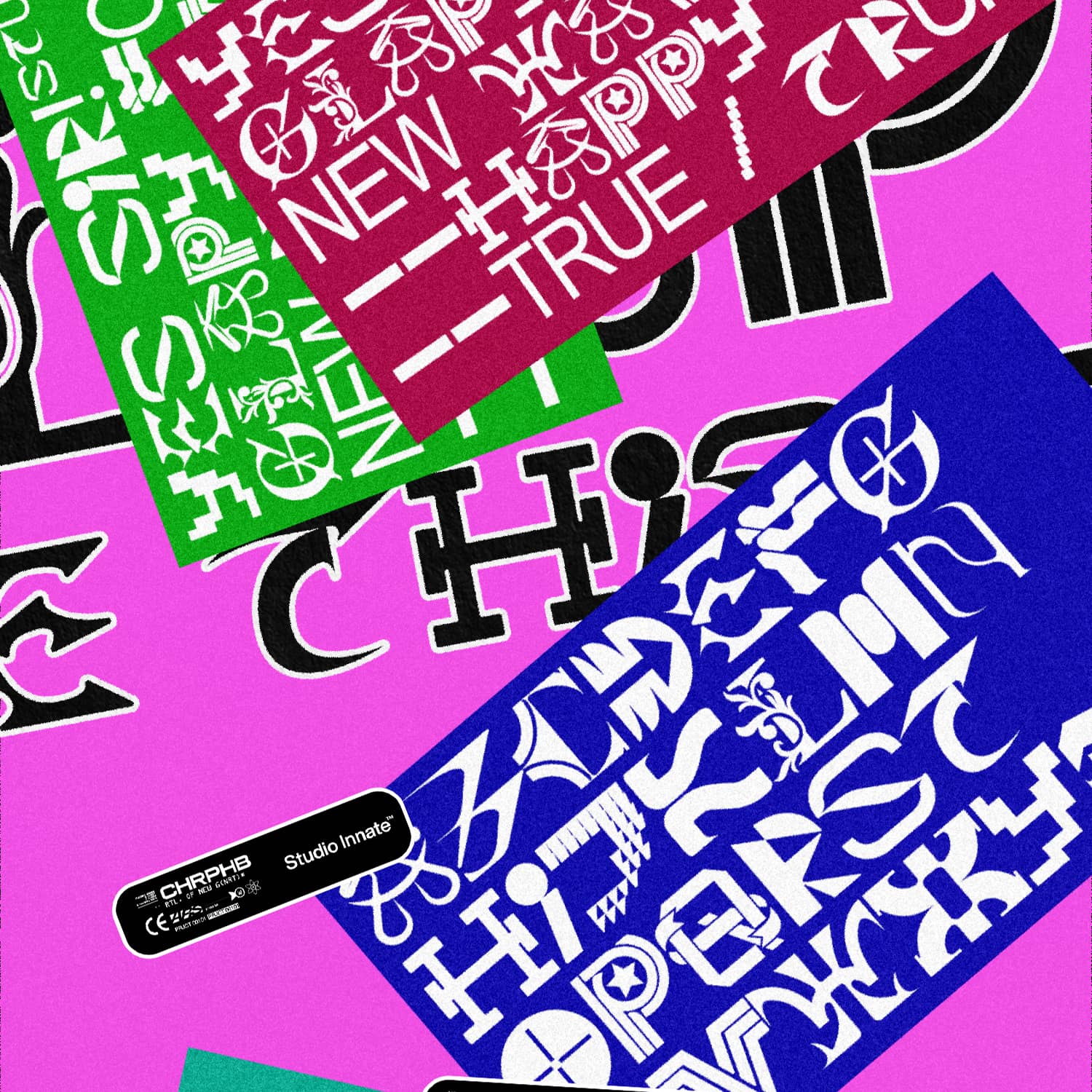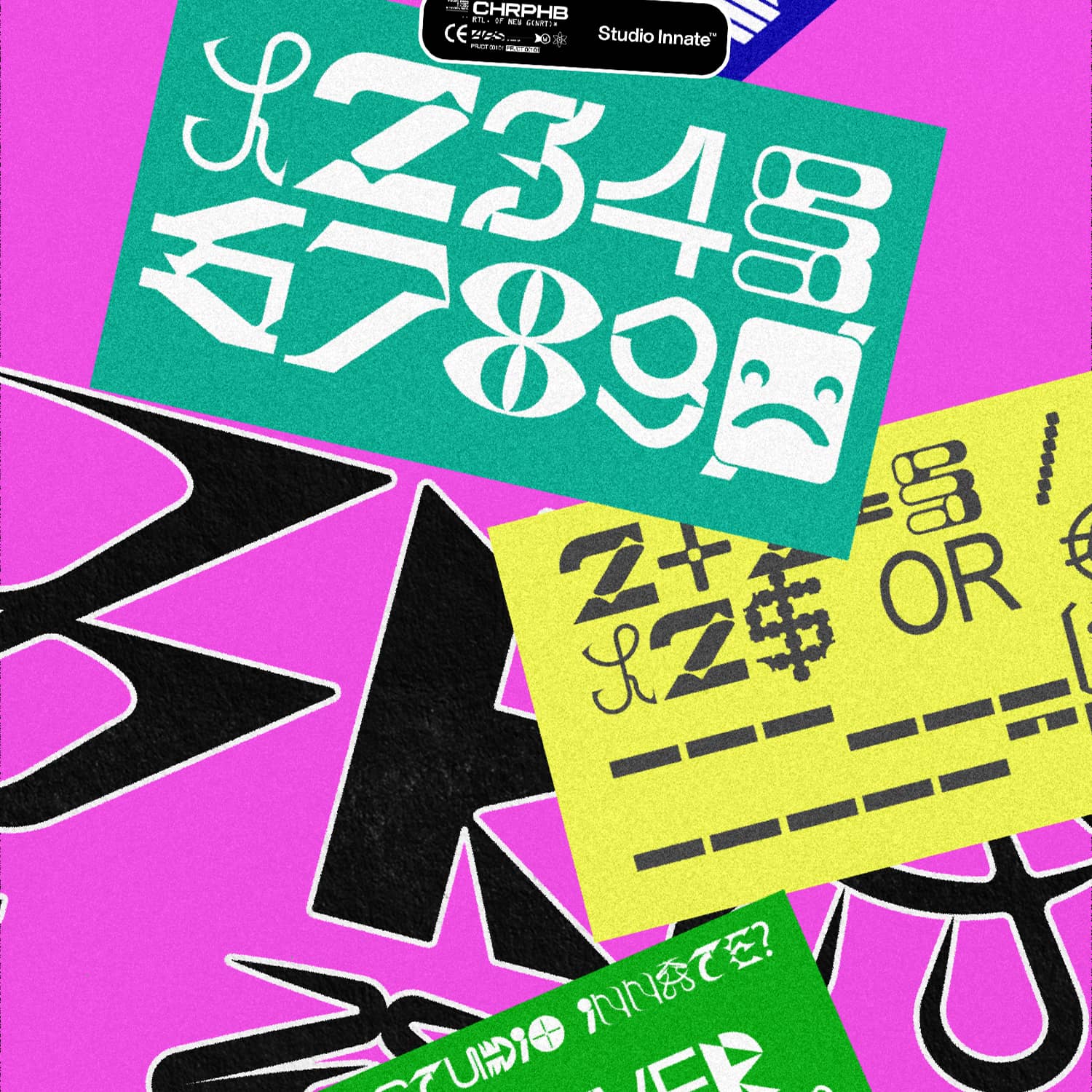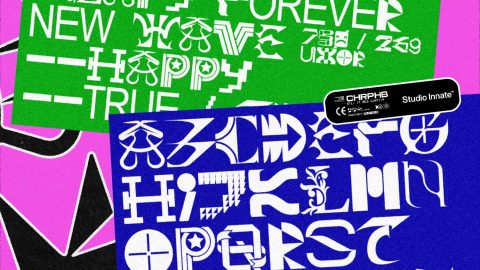
Khám phá Glapy Font , phông chữ hiện đại và vui nhộn với thiết kế “random” độc đáo. Hoàn hảo để thêm nét chơi đùa và phong cách đương đại vào mọi dự án sáng tạo của bạn!
1. Giới Thiệu Glapy Font
Bạn đang tìm kiếm một phông chữ mang lại sự tươi mới, vui nhộn nhưng vẫn giữ được nét hiện đại? Glapy Font chính là lựa chọn hoàn hảo dành cho bạn! Được phát triển bởi @chrphb, phông chữ này nổi bật với thiết kế “random” độc đáo, nơi mỗi ký tự, biểu tượng và con số đều được chế tác tỉ mỉ, mang đến cảm giác sống động và sáng tạo cho mọi thiết kế.
Với sự kết hợp giữa các chữ cái viết hoa cổ điển và kiểu dáng hiện đại, Glapy Font là công cụ lý tưởng để thêm phong cách vui tươi và cá tính vào bất kỳ dự án nào – từ poster, logo đến bao bì sản phẩm.
2. Đặc Điểm Nổi Bật Của Glapy Font
Thiết kế “Random” độc đáo : Mỗi ký tự đều có nét riêng biệt, tạo cảm giác ngẫu nhiên và thú vị.
Phong cách vui nhộn và hiện đại : Lý tưởng cho các dự án cần sự sáng tạo và năng động.
Hỗ trợ đa dạng ký tự :
- Chữ hoa (Uppercase)
- Chữ thường (Lowercase)
- Dấu phụ (Diacritics)
- Biểu tượng và số (Symbols & Numbers)
3. Thông Số Kỹ Thuật
- Trọng lượng (Weight) : Regular
- Hỗ trợ ký tự :
- Chữ hoa (Uppercase)
- Chữ thường (Lowercase)
- Dấu phụ (Diacritics)
- Biểu tượng và số (Symbols & Numbers)
- Ứng dụng : In ấn, thiết kế đồ họa, web design, mockup sản phẩm, và nhiều hơn nữa.
4. Ứng Dụng Thực Tế
- Thiết kế đồ họa : Tạo poster, bao bì, hoặc logo với phong cách vui nhộn và hiện đại.
- Chỉnh sửa ảnh : Thêm văn bản nghệ thuật vào hình ảnh với nét chữ độc đáo.